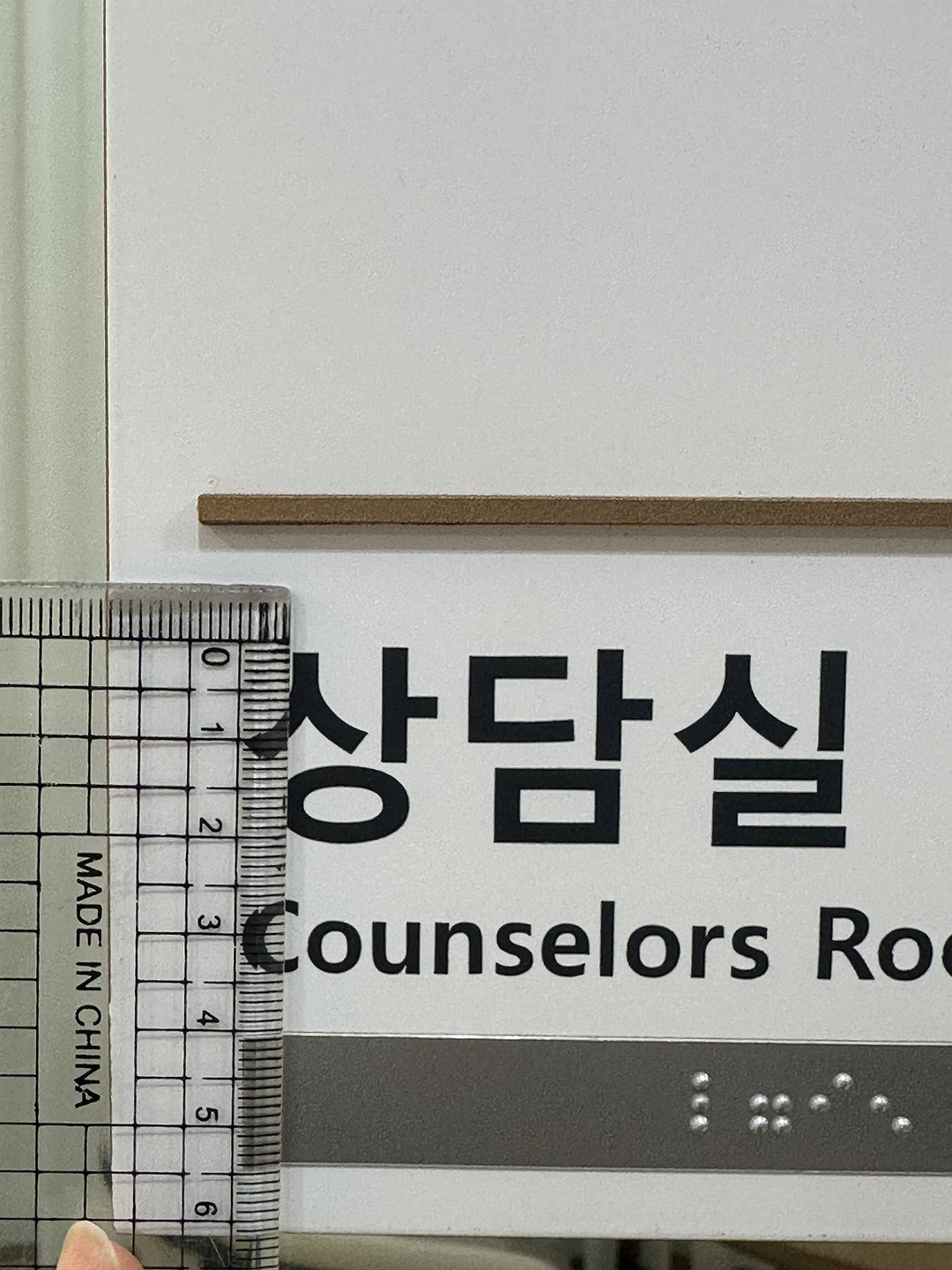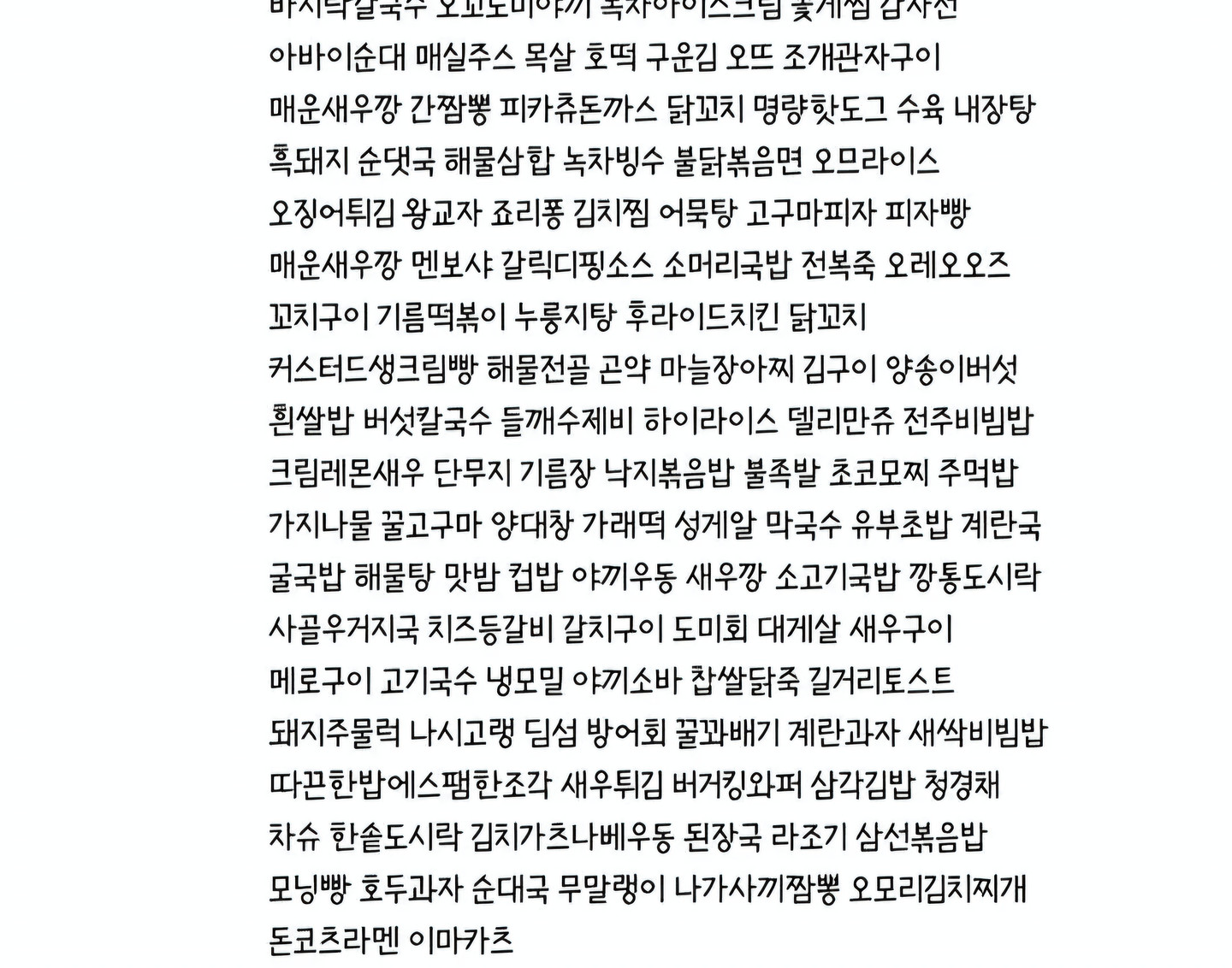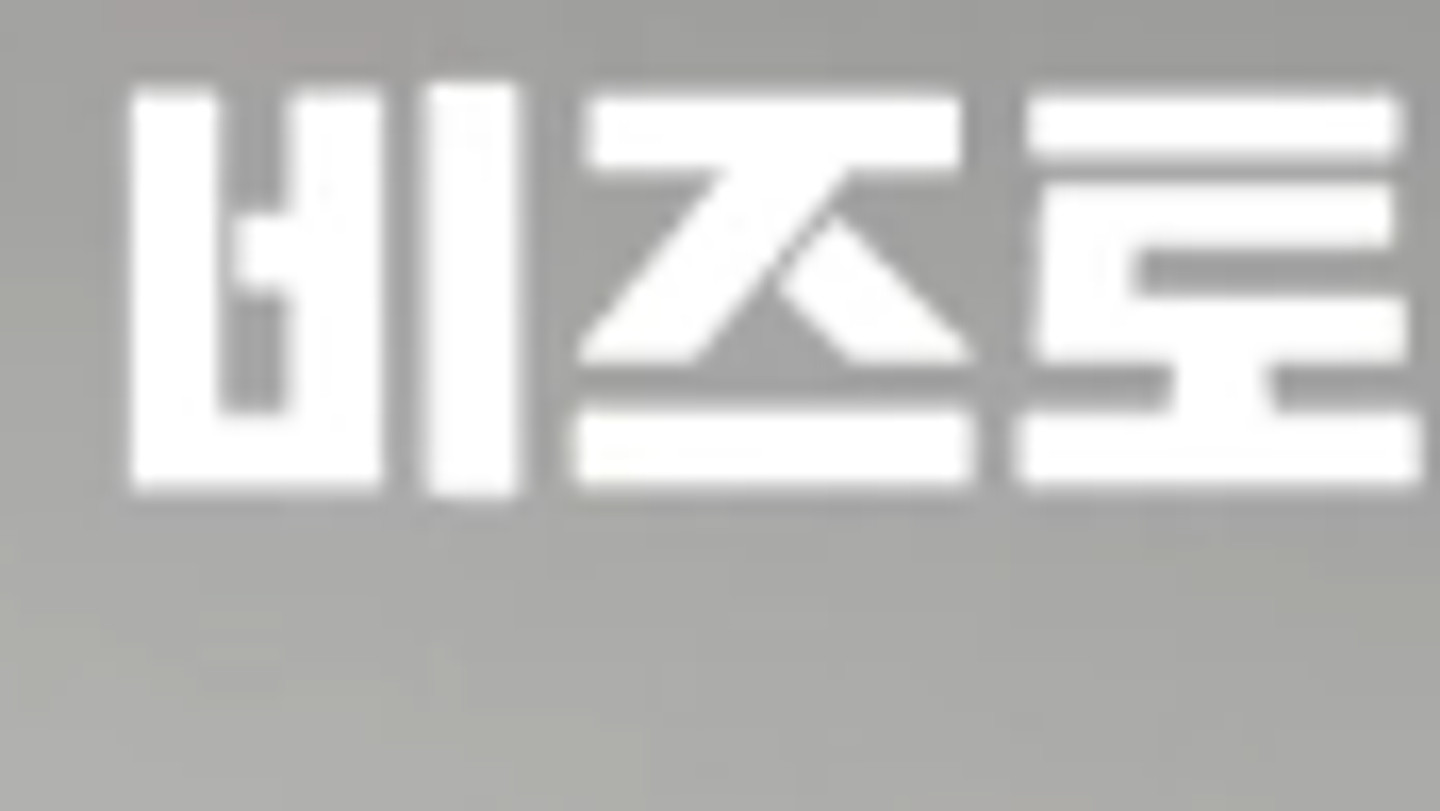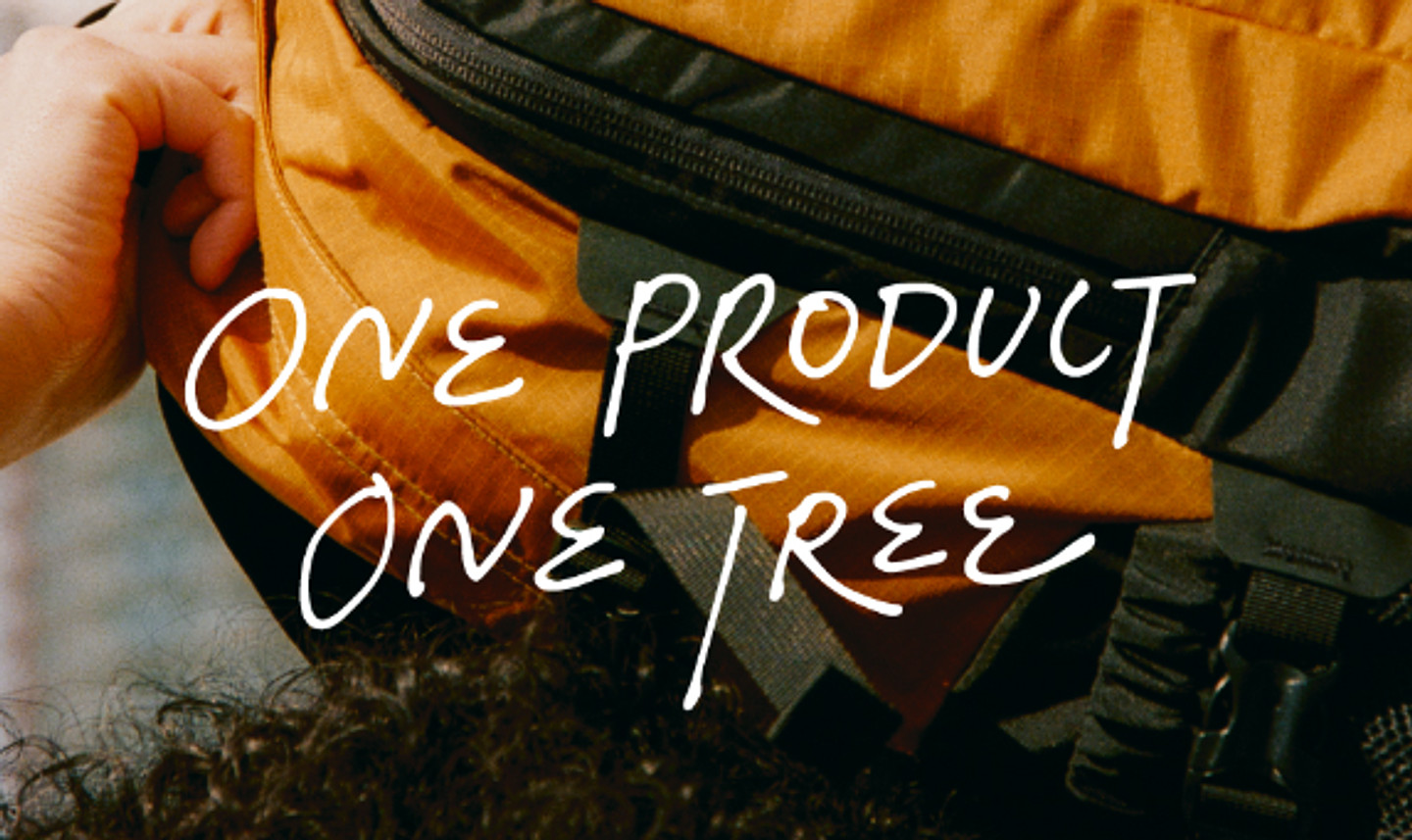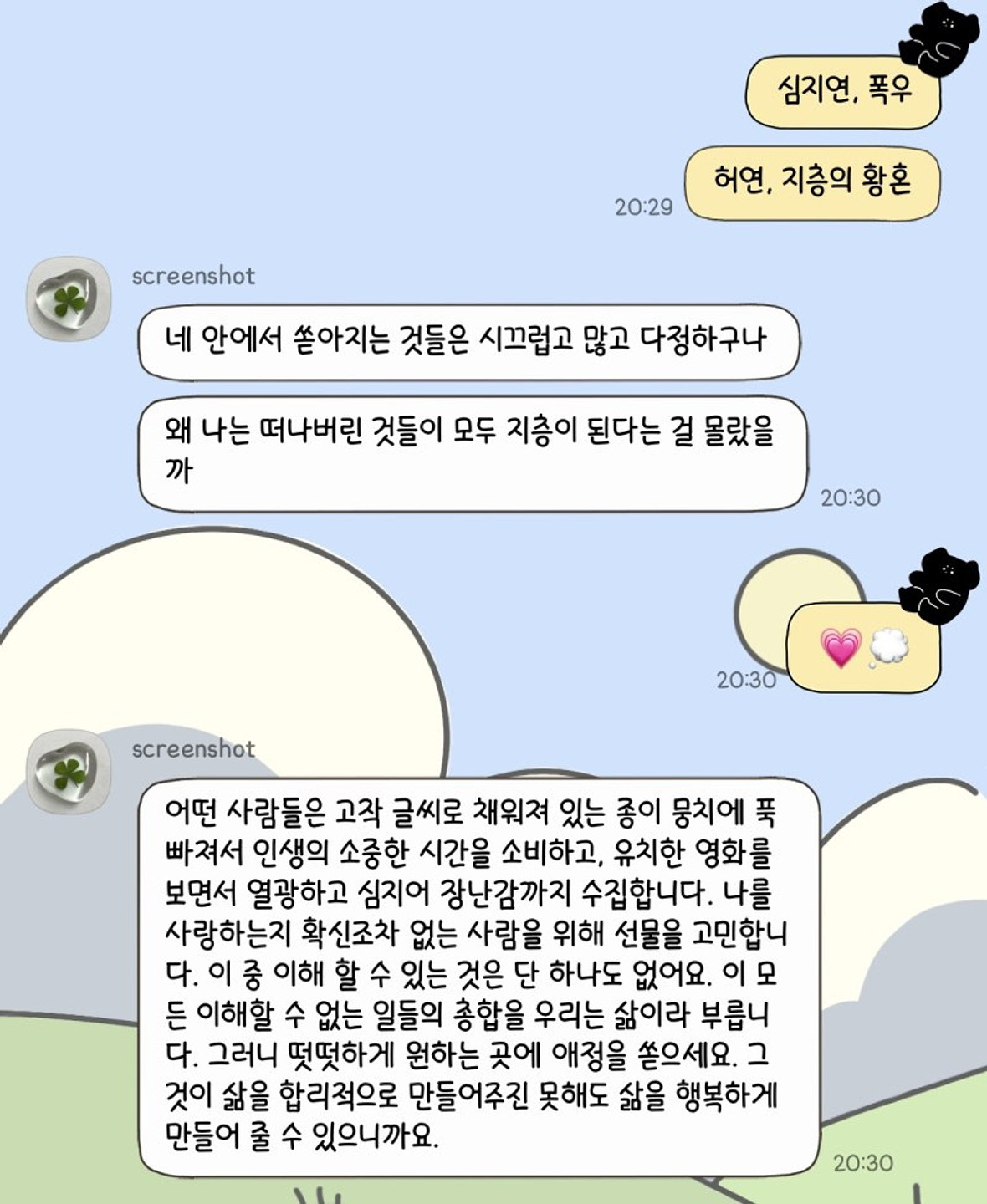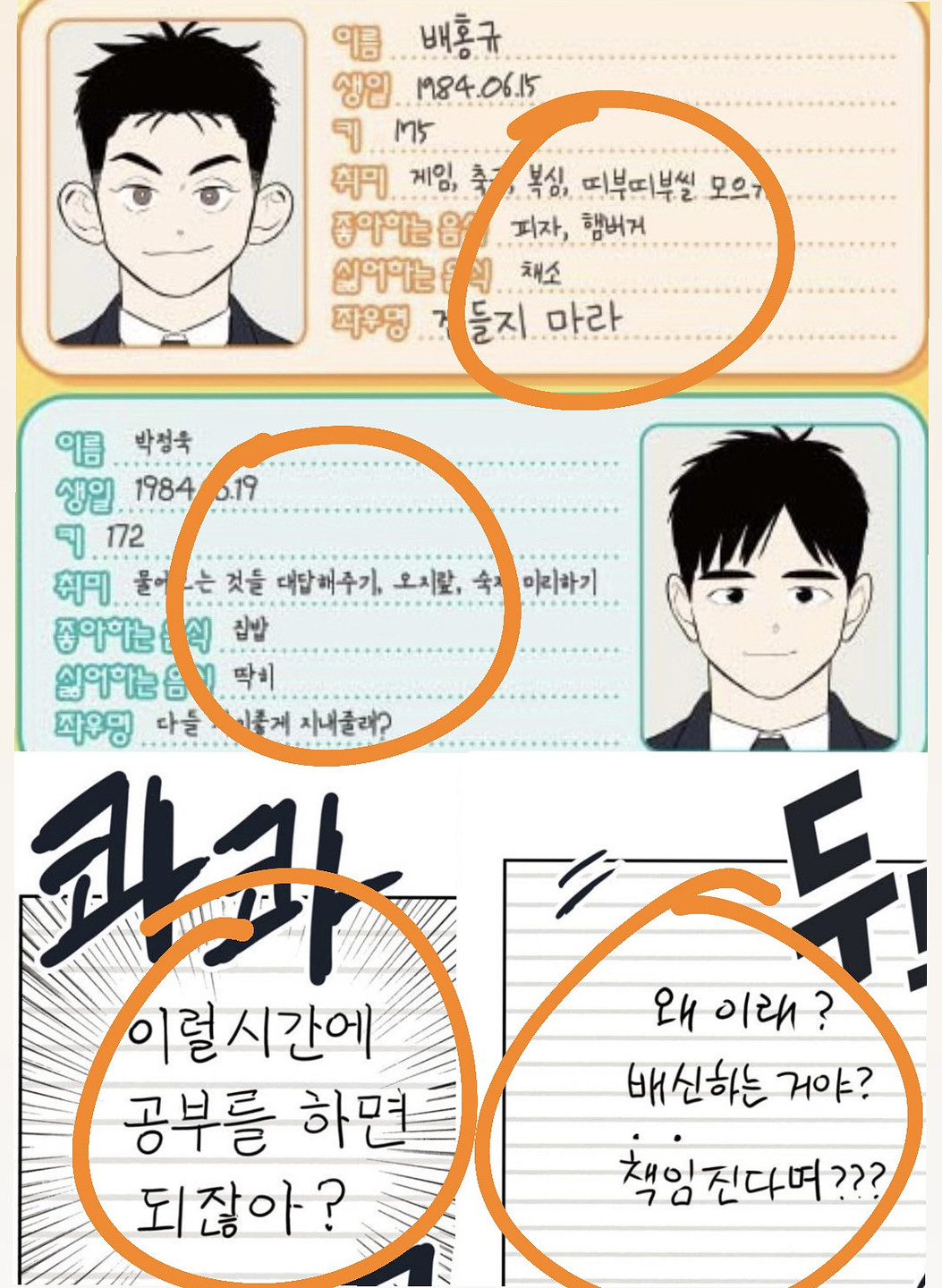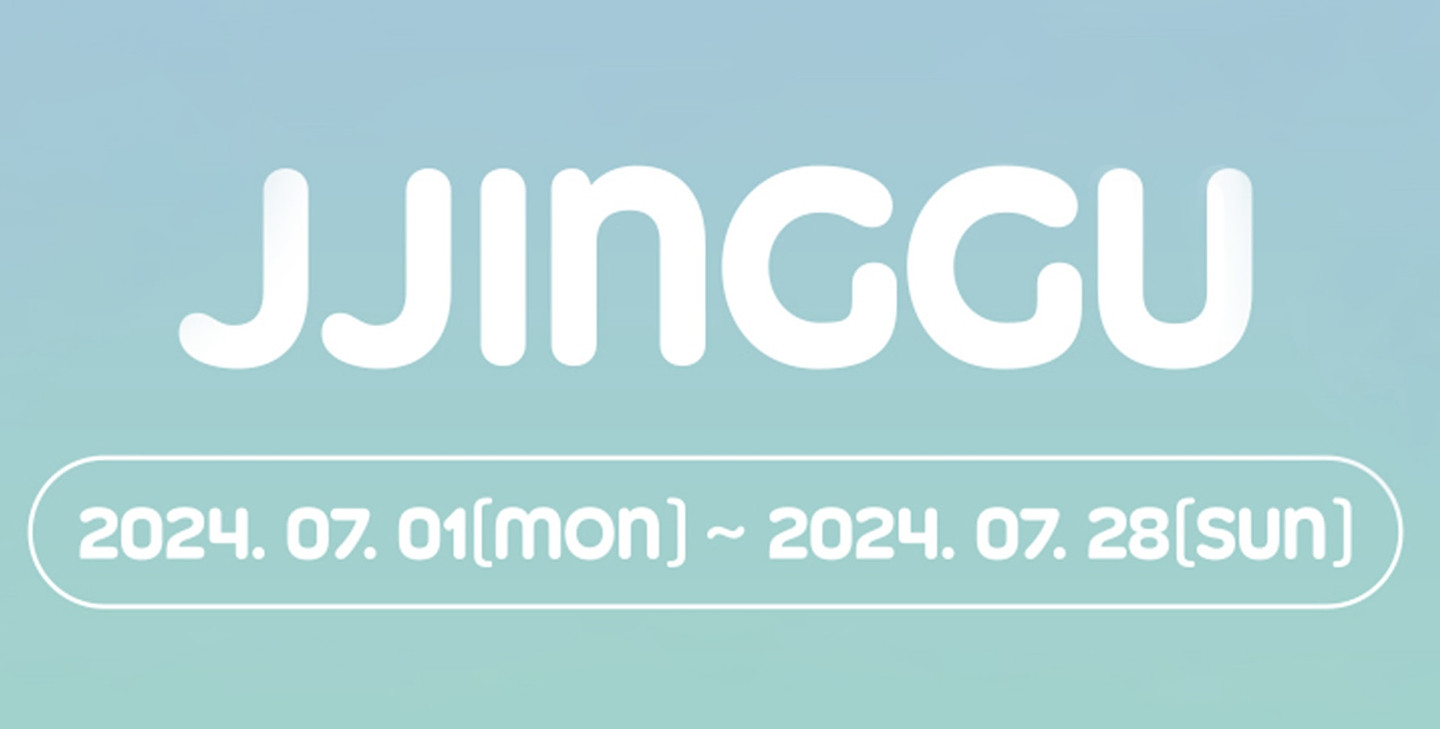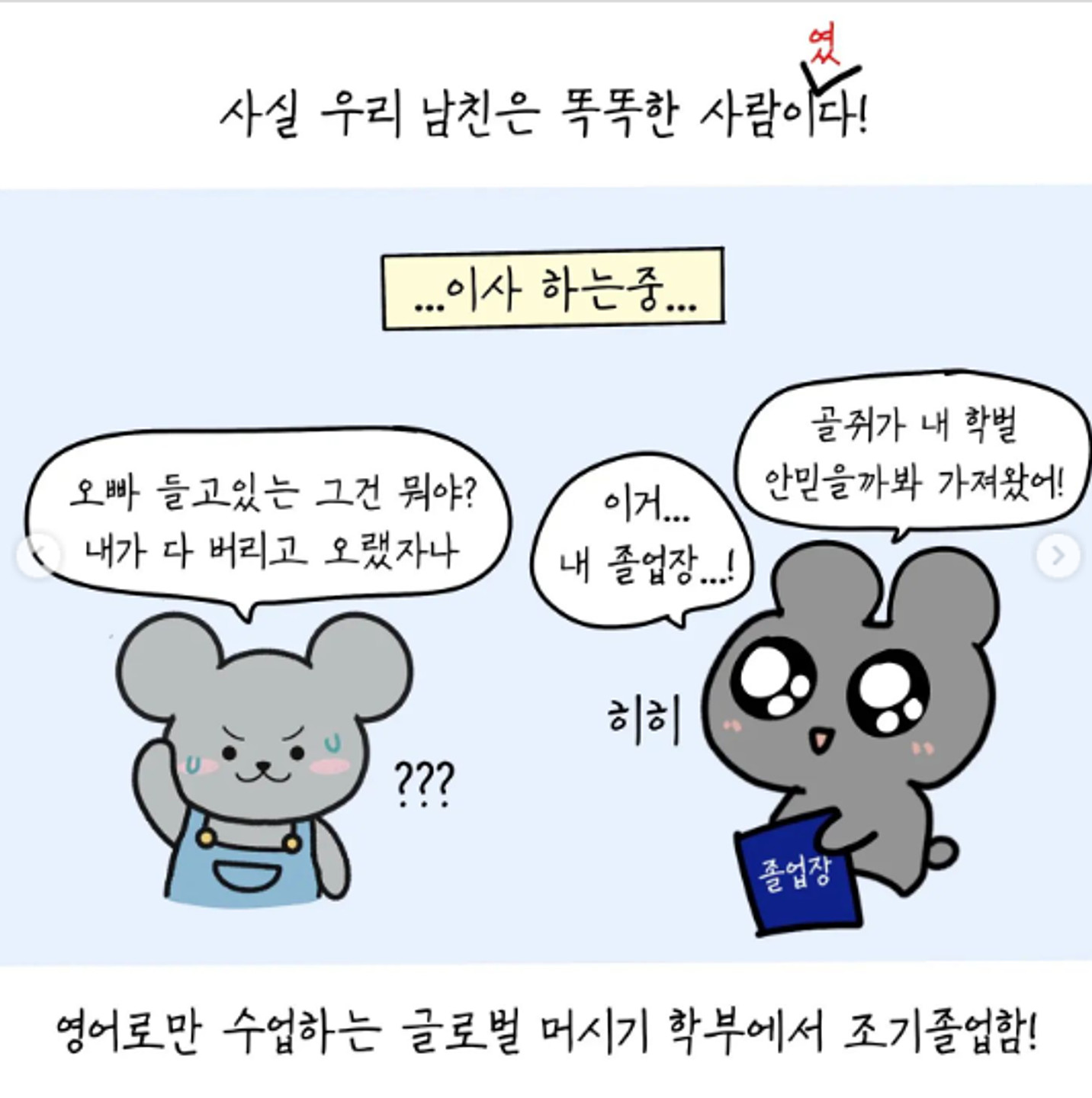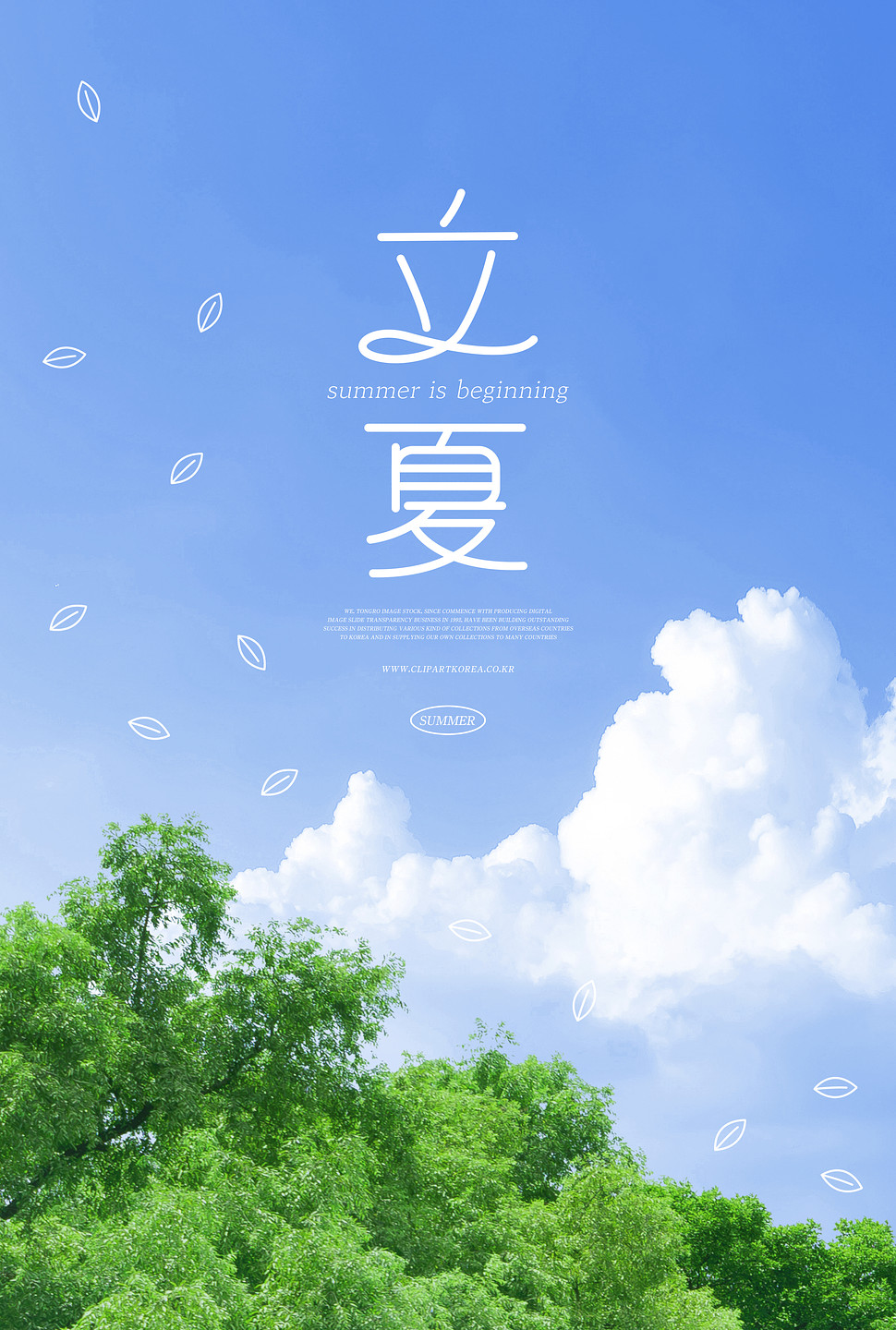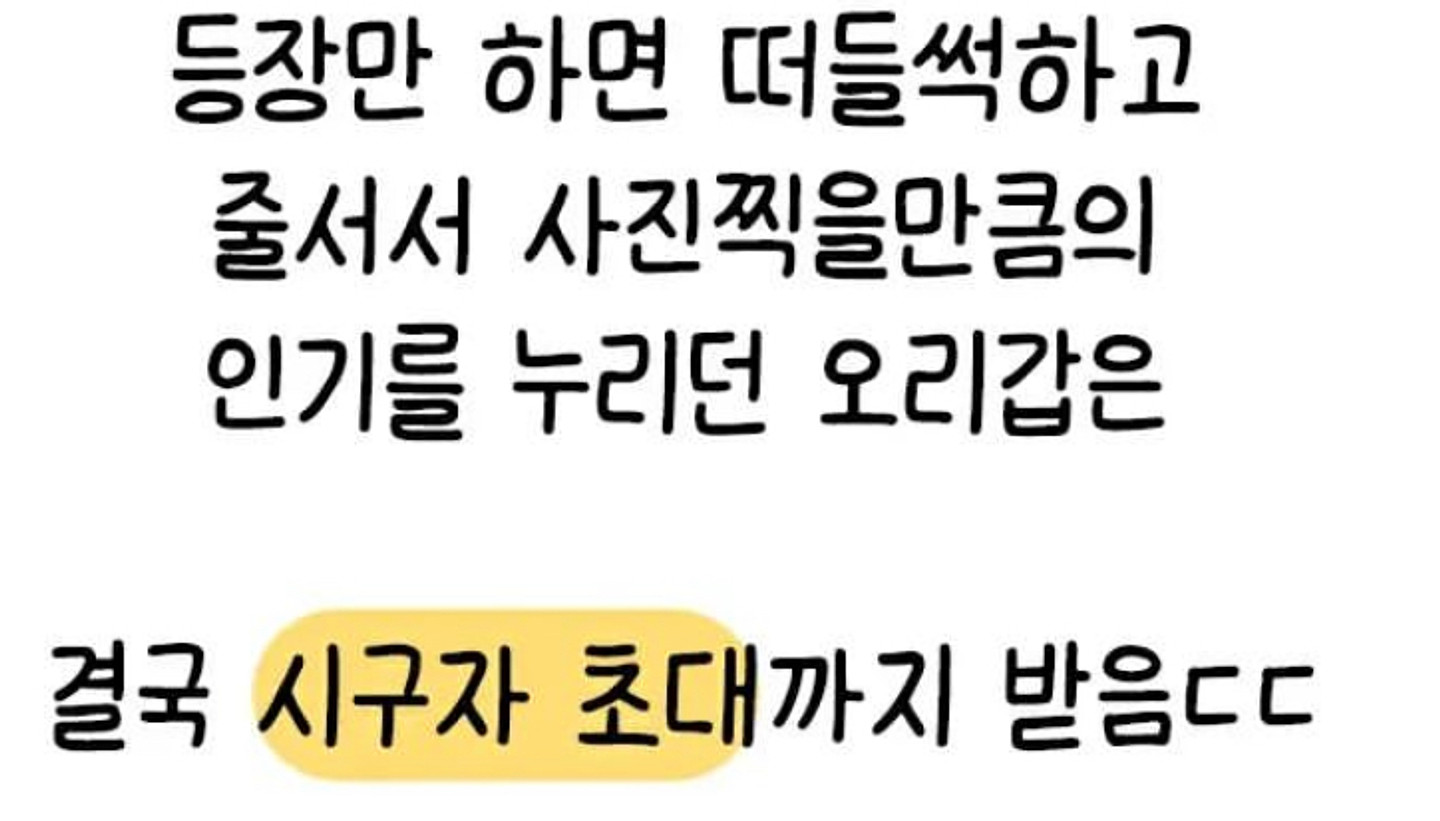
아무리 찾아도 비슷한거 밖에 안나와서... 혹시 아시는 분 계실까요? 위 아래 둘다 알려주시면 감사하겠습니다
혹시 무슨 폰트인지 알 수 있을까요?? 정말 알고싶어요ㅜㅜ
폰트이름이머죠ㅠㅠㅠ? 찾아도안나와소
전에쓰던폰트인데 폰트삭제하고나서 다시찾아보려니 안나와요 무슨 폰트인지아시는분
혹시 이 폰트에 대해서도 좀 알 수 있을까요?
이 폰트 알 수 있을까요?>
이 폰트 궁금해요 아시는 분!!
무슨 폰트인지 궁금해요! 비슷한 폰트도 괜찮아요
이 폰트 뭘까요? 굵으면서도 감성있는
유튜브에서 보다가 좋은 폰트를 찾았는데 이 폰트가 뭔지를 모르겠어요
로고 폰트가 궁금합니다. 유사한 폰트를 대조해도 아닌것 같대요 ㅠㅠ
이 폰트 좀 찾아주세요! ㅠㅠ 정확히 일치하는 게 없네요..
주토피아 폰트 뭔지 알 수 있을까요?
요새 자주보이는 폰트같은데 찾기가 어렵습니다ㅠㅠ 무슨폰트일까요?
무슨 폰트인지 궁금해요!!
폰트 궁금합니다 😭
이거 무슨 폰트인지 너무 궁금합니다! 제발 알려주세요..
이 폰트 뭔지 알 수있나요?
제작된 폰트일까요?.?
이 폰트 지마켓산스인가요?
영어 서체 궁금합니다...! 어도비폰트인가요?
고딕 기울여서 쓴건가요? 궁금합니다!
이거 서체인가요..? 손글씨인가요
이 서체 궁금합니다! 고딕인가요..?
여기 안내문 폰트가 뭔지 알 수 있을까요?
폰트 이름 아시는 분 답변 부탁드립니다. ㅠㅠ
이 폰트 이름 알려주세요 ,,
'이든한끼' 폰트 및 '매일매일 정성깃든 반찬거리' 폰트가 무엇인지 궁금합니다.
이거 무슨 폰트일까요?? 혹시나 아시는 분이 있다면, 알려주시면 감사하겠습니다!
이 폰트 뭔지 알려주실 수 있을까요🥹
음악방송 폰트 좀 찾아주세요..ㅠㅠ 겉에 테두리도 몇인지 모르겠어요..
이탤릭효과 넣은 것도도 아닌 게 이게 무슨 폰트인가요?
와키윌리 광고! 자막 폰트 궁금해요
굴림체 비슷한 느낌인데 어떤 폰트일까요
사진처럼 Sandoll 프레스 02 Basic와 비슷한 폰트 있을까요? 월 6천원이라 무료로 찾고싶어요
포켓몬 폰트 이거 뭔가요 ㅠㅠ
폰트 이름좀 알려주세요~
무슨폰트일까여여여여
시청해주셔서 감사합니다<< 이폰트 뭔가요?
Toxic till the end 폰트 뭔지 아시는분 ㅠㅠ
유튜브에서 되게 많이 보이는 폰트에요.. 에버랜드 유튜브채널에 올라오는 푸바오 영상에서도 봤었는데.. 꼭 찾고싶습니다.
폰트이름이 궁금합니다
이 폰트 정보가 궁금합니다 !
무슨 폰튼가요?
해외축구, 농구 부분 폰트가 궁금해요 네이버다 보니 관련 폰트일걸 같은데 어떤걸까요?
무슨폰트인지 궁금합니다.
폰트 알려주세요!
한글자막 무슨 폰트인가용??
트위터에서 라벨 스티커용으로 많이 사용하는 폰트 같은데 뭔지 너무너무 궁금해요!!
당아비분향니 : 너에게로 달려갈게 드라마 오프닝 한글 자막인데요! 대체 어떤 폰트인가요? 🥲
이 폰트 뭘까요? 아무리 검색해도 안 나와서 글 남깁니다 ㅜㅜ
폰트 알려주실 수 있나요???
미리캔버스에서 명함 디자인 하다 찾은 폰트인데 구글이랑 다 검색해 봐도 무슨 폰트인지 알수가 없네요. 제발 찾아주세요! ㅠㅠ 정말 이뻐서 어디까지 사용할 수 있는지 궁금한 폰트입니다.
이 폰트 뭔가용? 찾아주시면 너무너무 감사할 것 같아요ㅠㅠ
우연히 유튜브 보다가 발견했는데 이 폰트 뭔가요?
폰트이름 아시는 분.. 부탁드려요😭